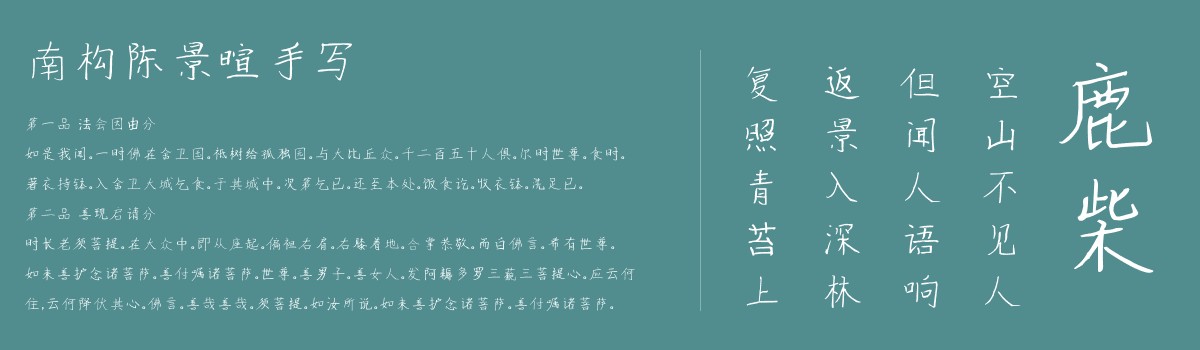
南构陈景暄手写
作者介绍:陈景暄,2010年出生于杭州,目前就读于文澜未来科技城蔚澜小学。性格阳光,兴趣爱好比较广泛,其中阅读与足球是最爱,另外围棋、编程、吉它、羽毛球等也颇为喜欢。
南构陈景暄手写是一款非常不错的艺术字体,由南构字库出品,用笔流畅随性,个性醒目,适应于报纸和杂志和书籍中常用字体, 海报、个性促进品牌标志设计、字体设计、等环境使用,欢迎喜欢的朋友前来字体家下载使用。